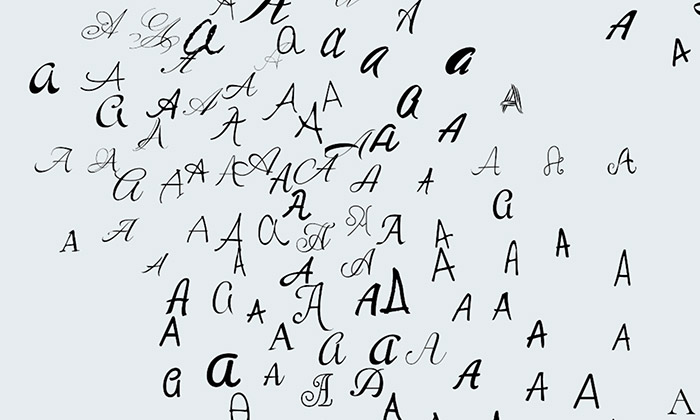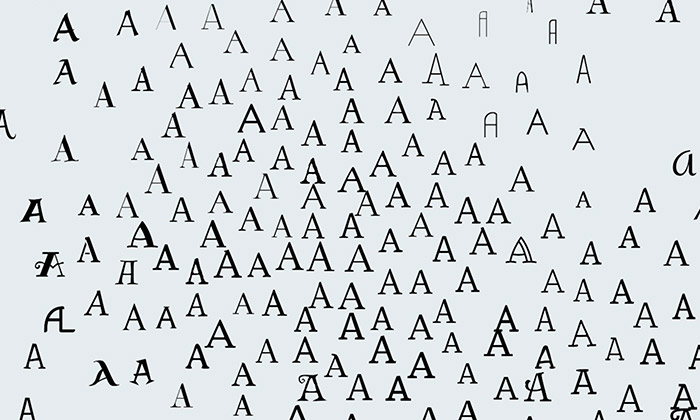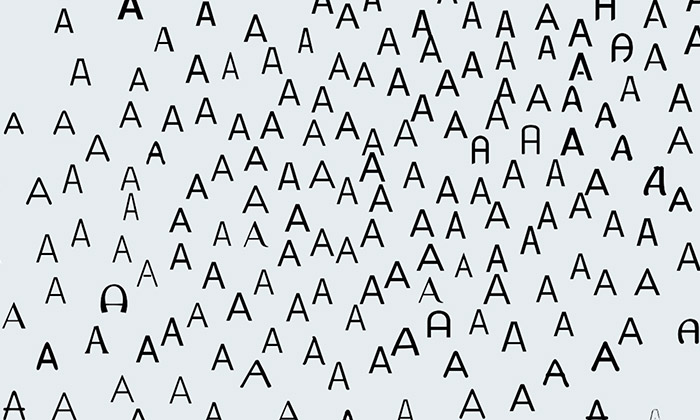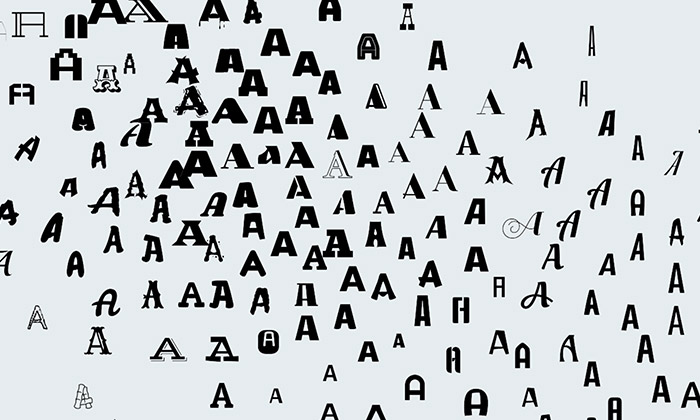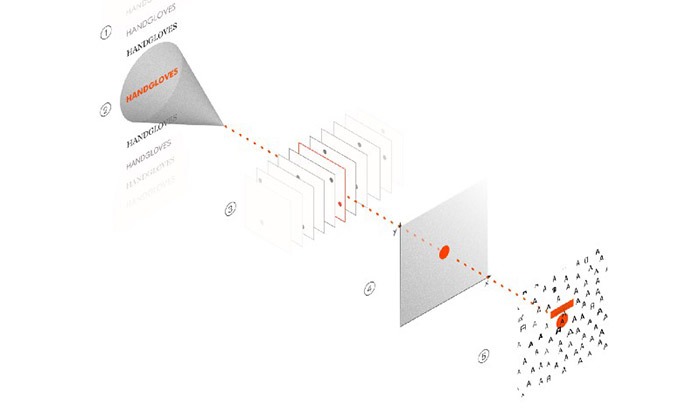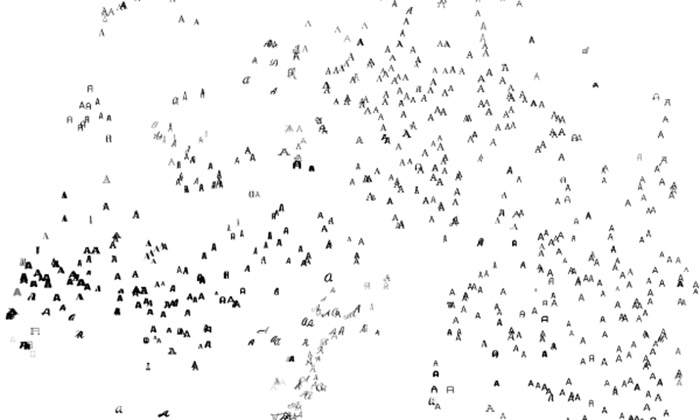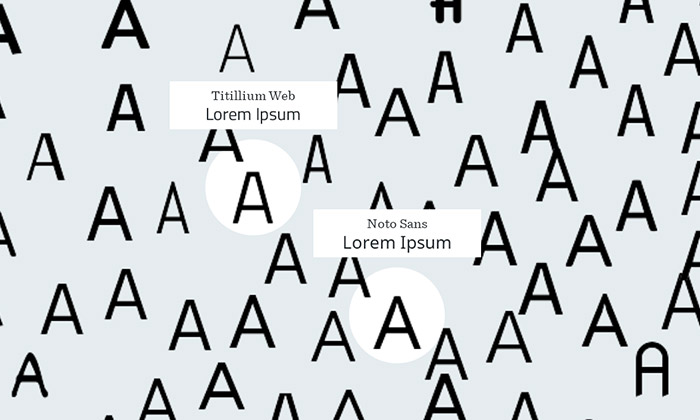
Mezinárodní designérská společnost IDEO vyvinula interaktivní mapu písem nazvanou Font Map. Na jedné stránce se inteligentně seskupují stovky typů písem do skupin, aby pomohly grafickým designérům i dalším profesím s výběrem vhodného písma.
IDEO se zaměřuje na navrhování různorodých řešení od produktového designu a inovací až po grafický a obalový design. Nejen pro sebe, ale veřejně bezplatně pro každého navrhli Font Map, užitečný nástroj, který má pomoci všem, kteří si neví rady s vhodným výběrem písma.
Jednoduše navržená interaktivní stránka nabízí seskupení několika set písem zastoupených úvodním písmenem A. Po najetí na jednotlivé písmeno se ukáže název písma a zkušební nápis vyvedený právě ve vybraném písmu. Uživatel si tak rychle může vybrat své vysněné písmo, případně alternativu.
Nástroj je navíc důmyslnější a dokáže písma vyhledávat či hledat podobná. Celkem 750 písem je seskupováno podle předem zadaných parametrů inteligentně, takže bezpatková písma najdete všechny pohromadě stejně jako patková či grafická. Věříme, že se takto užitečný nástroj uchytí, rozroste a stane se každodenní součástí pracovního života všech designerů.